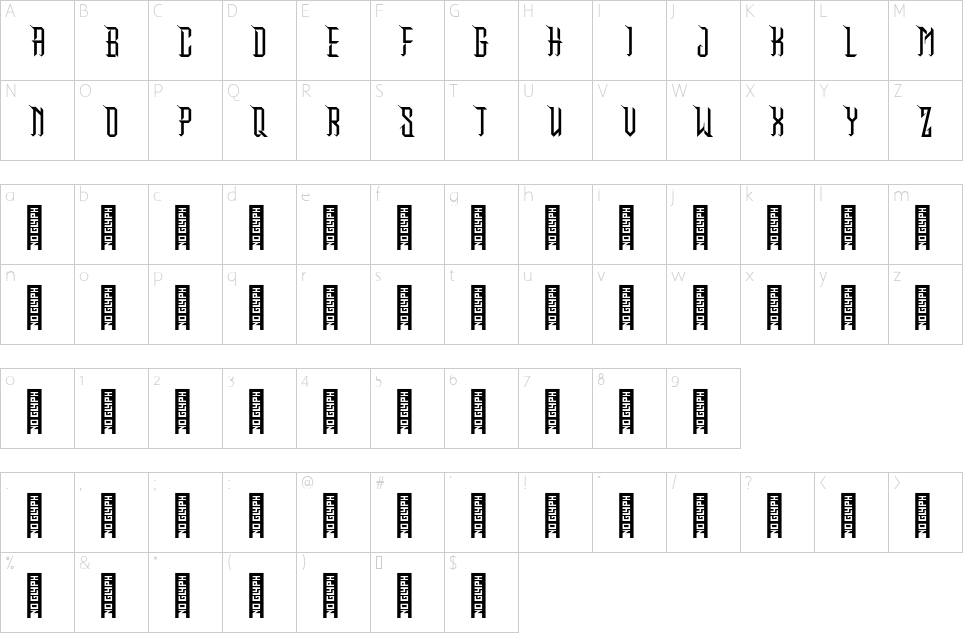
A fonte Makunu Black Letter é uma opção ideal para quem busca estilo e elegância em projetos de design. Ela foi criada pelo designer Chococreator, trazendo uma escrita robusta e imponente que se destaca em qualquer projeto. Esta fonte, que já foi baixada 3.789 vezes, é uma excelente escolha para quem procura um tom mais sóbrio e elegante. Seja para rótulos de embalagens, design editorial ou até mesmo para criação de logotipos, Makunu Black Letter traz uma personalidade única que irá complementar qualquer projeto. Se você está procurando por uma fonte de qualidade para seu trabalho de design, Makunu Black Letter é uma ótima opção. Não perca tempo e descubra por si mesmo o poder desta fonte.